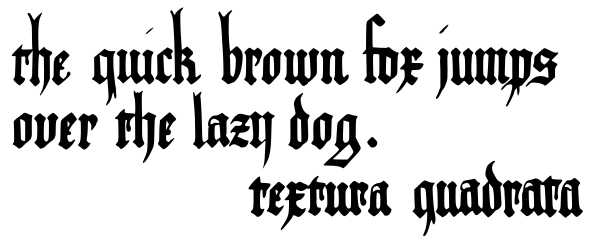
Текстура (шрифт)
Тексту́ра (от лат. textura — ткань) — первая и основная разновидность готического письма. Своё название текстура получила за то, что покрывала страницу равномерно. Характерное отличие шрифтов данного типа — вытянутость букв.